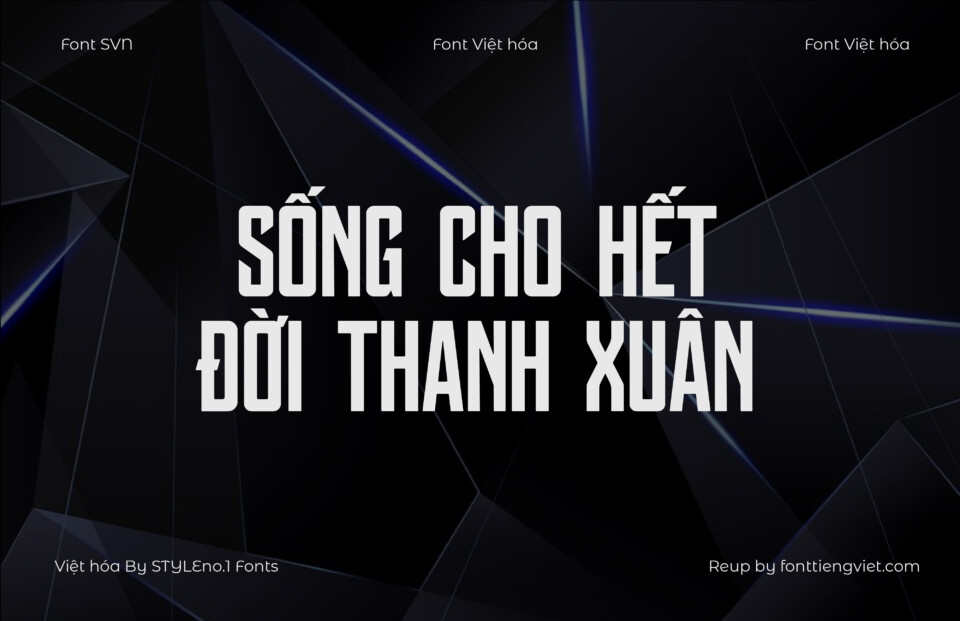
Font Việt hóa SVN Justice League
Trong thế giới đồ họa hiện đại, việc tìm kiếm một bộ Font Miễn Phí có phong cách mạnh mẽ luôn là ưu tiên hàng đầu của các nhà thiết kế trẻ. Font Việt hóa SVN Justice League nổi lên như một lựa chọn hoàn hảo, mang đậm phong cách siêu anh hùng từ vũ trụ DC Comics. Đây là bộ font chữ đặc biệt, giúp các bài thuyết trình hay dự án học đường của học sinh trở nên sinh động và lôi cuốn hơn bao giờ hết. Với sự hỗ trợ đầy đủ dấu tiếng Việt, người dùng có thể thoải mái sáng tạo nội dung mà không lo lỗi hiển thị.
Đặc điểm nổi bật của Font Việt hóa SVN Justice League
Thiết kế đậm chất điện ảnh và hiện đại
Bộ font này mô phỏng phong cách chữ của các chiến binh công lý, với những đường nét góc cạnh, dày dặn và cực kỳ vững chãi. Font Việt hóa SVN Justice League không chỉ mang lại cảm giác quyền lực mà còn thể hiện sự chuyên nghiệp trong từng nét chữ. Các bạn học sinh có thể sử dụng font này để làm tiêu đề báo tường, bìa tiểu luận hoặc các ấn phẩm truyền thông cho câu lạc bộ trường học. Sự rõ ràng của bộ font giúp thông điệp truyền tải nhanh chóng và gây ấn tượng thị giác mạnh.
Khả năng ứng dụng linh hoạt trong học tập
Ngoài mục đích giải trí, bộ font còn rất hữu ích trong việc giảng dạy và học tập sáng tạo. Giáo viên có thể dùng font chữ này để thiết kế các bảng vinh danh hoặc tài liệu học tập trực quan sinh động. Việc cài đặt font cũng rất đơn giản trên các phần mềm phổ biến như Word, PowerPoint hay Photoshop, giúp mọi người dễ dàng tiếp cận công nghệ thiết kế mới nhất hiện nay.